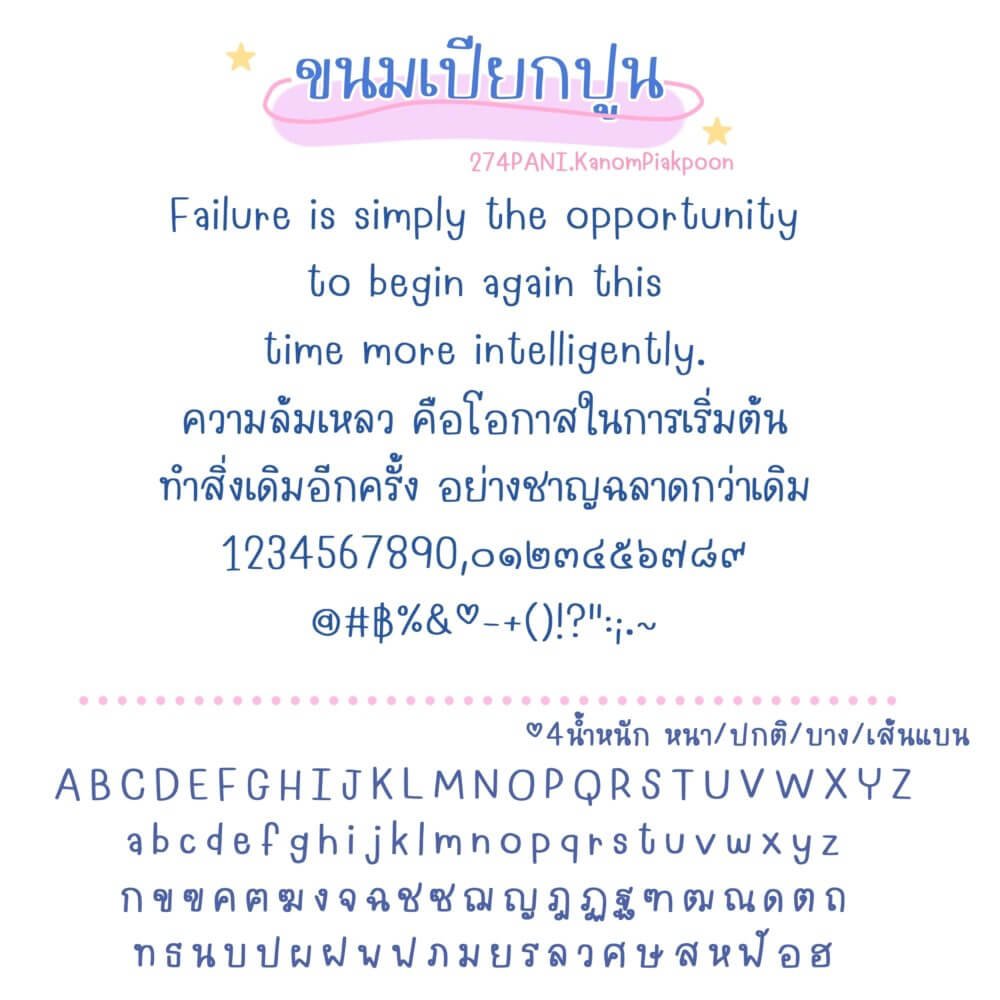
ขนมเปียกปูน (274PANIKanomPiakpoon)
แจกฟรี 1 น้ำหนักค่า (สำหรับใช้งานส่วนตัวเท่านั้น) ชุดนี้เป็นฟอนต์เรียบร้อยกึ่งทางการค่ะ ใช้งานได้หลายรูปแบบ ใครชอบฟอนต์แอนสไตล์นี้ โหลดฟรี! ไปทดลองใช้ก่อนได้ค่ะ
ฟอนต์มี 4 ไฟล์ 4 น้ำหนัก บาง ปกติ หนา เส้นแบน